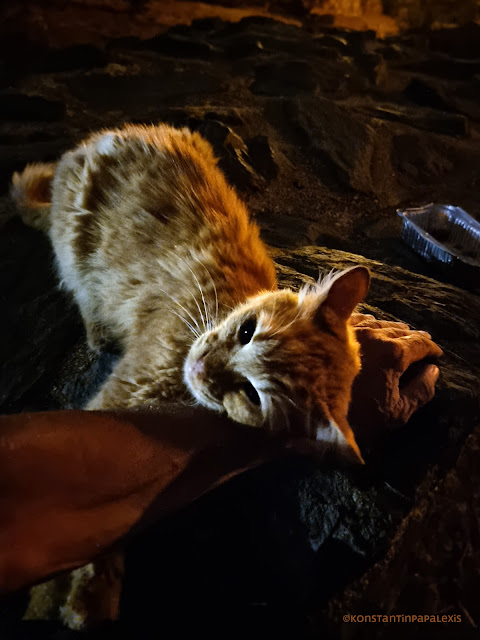
Βίκυ
Μέσ' τη νύχτα νομίζεις ότι δε σε βλέπουνε, και γενικώς ο αυτοέλεγχος χαλαρώνει, οπότε μπορεί να πάρεις και στάσεις όχι πολύ κανονικές. Εντάξει. Δε χαλάει κι ο κόσμος.
Παιδιά, από δω ή Βίκυ. Βίκυ, τα παιδιά.